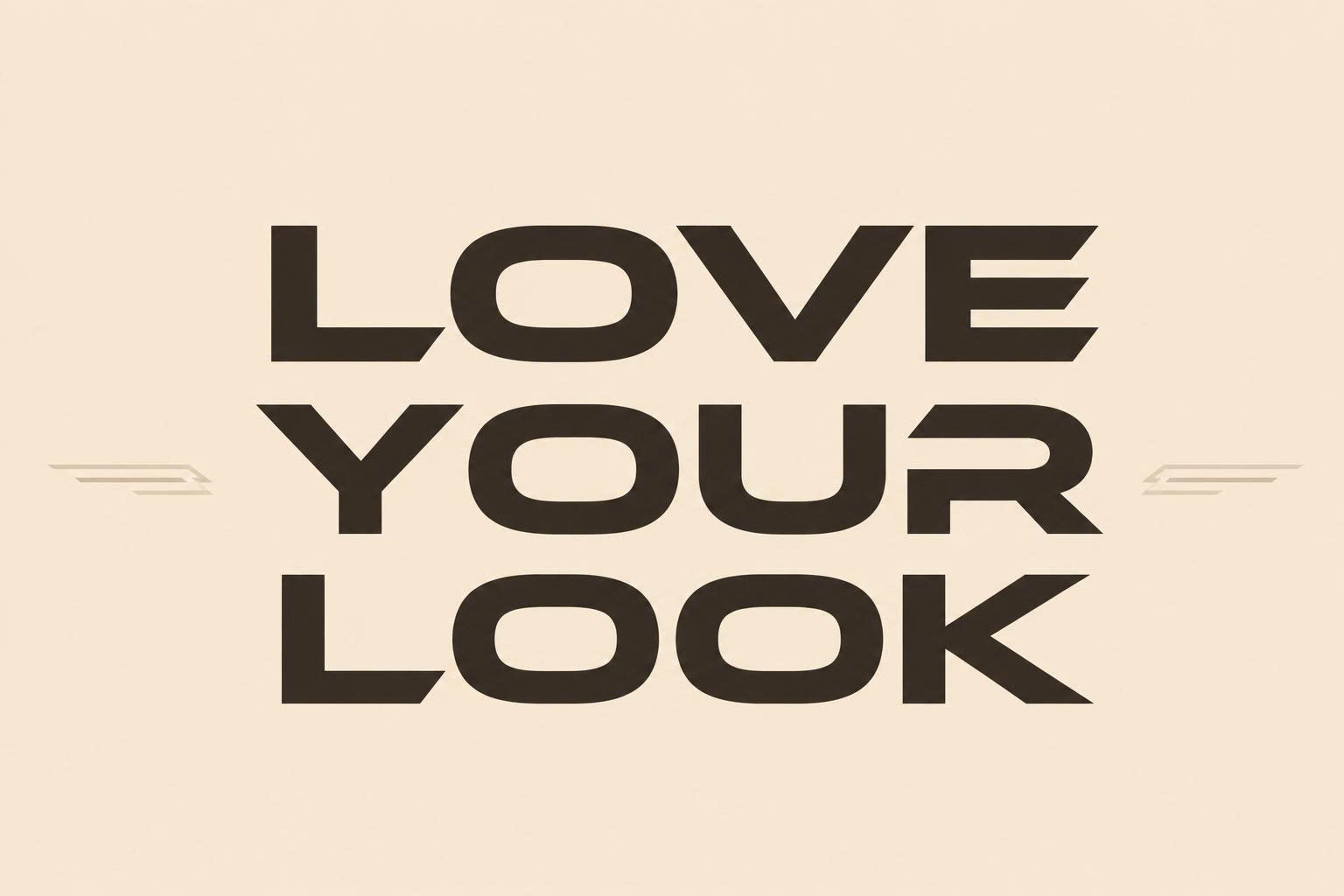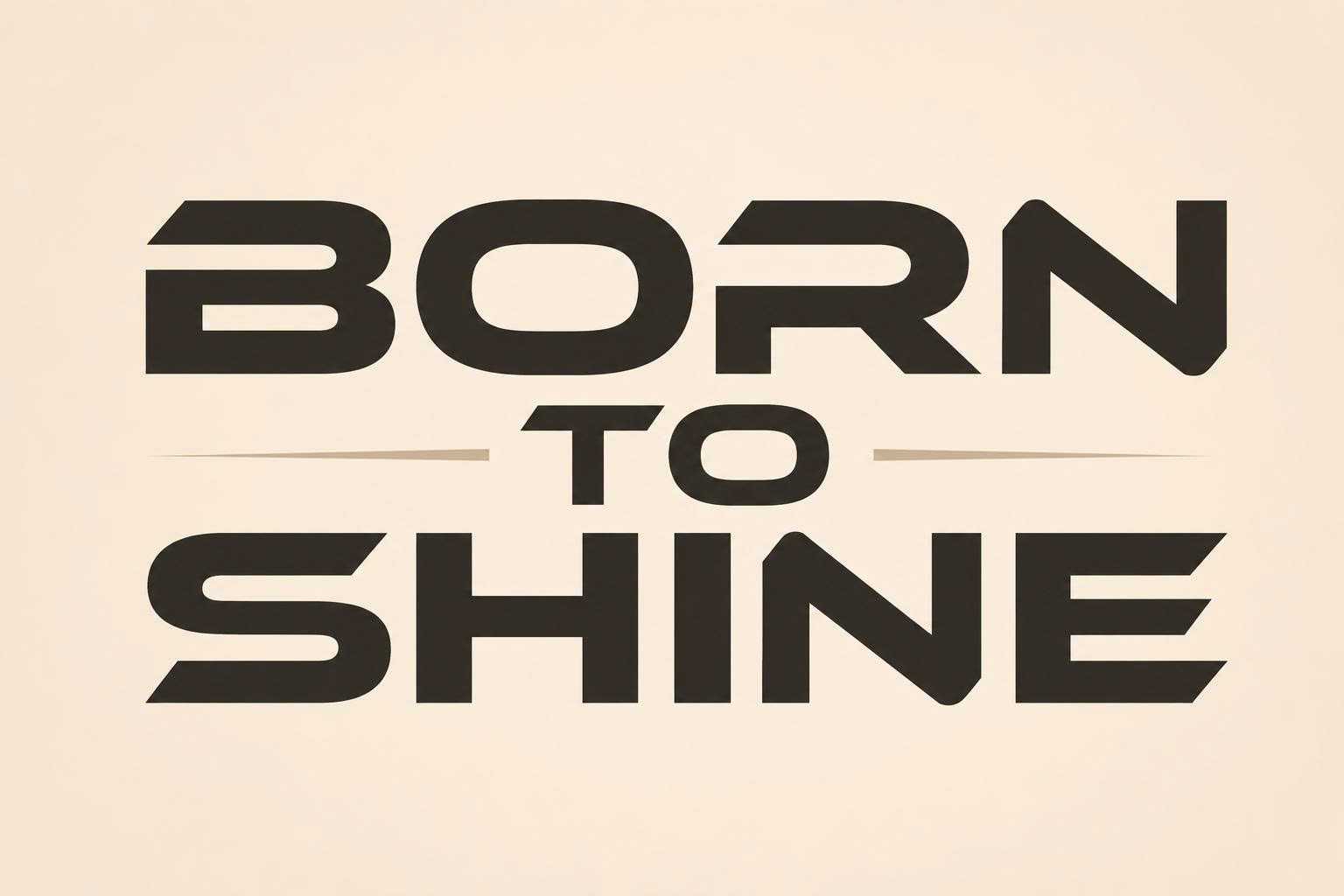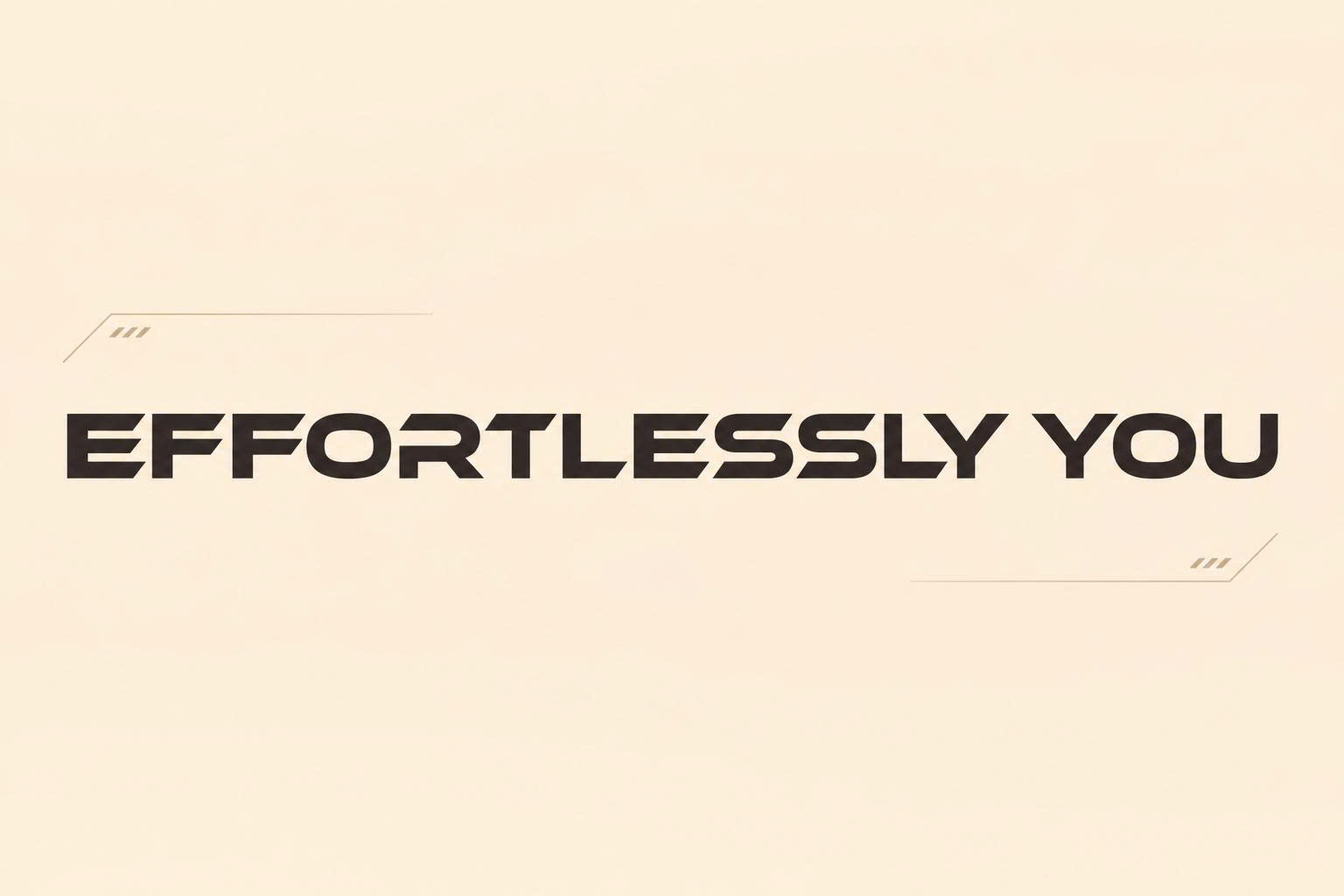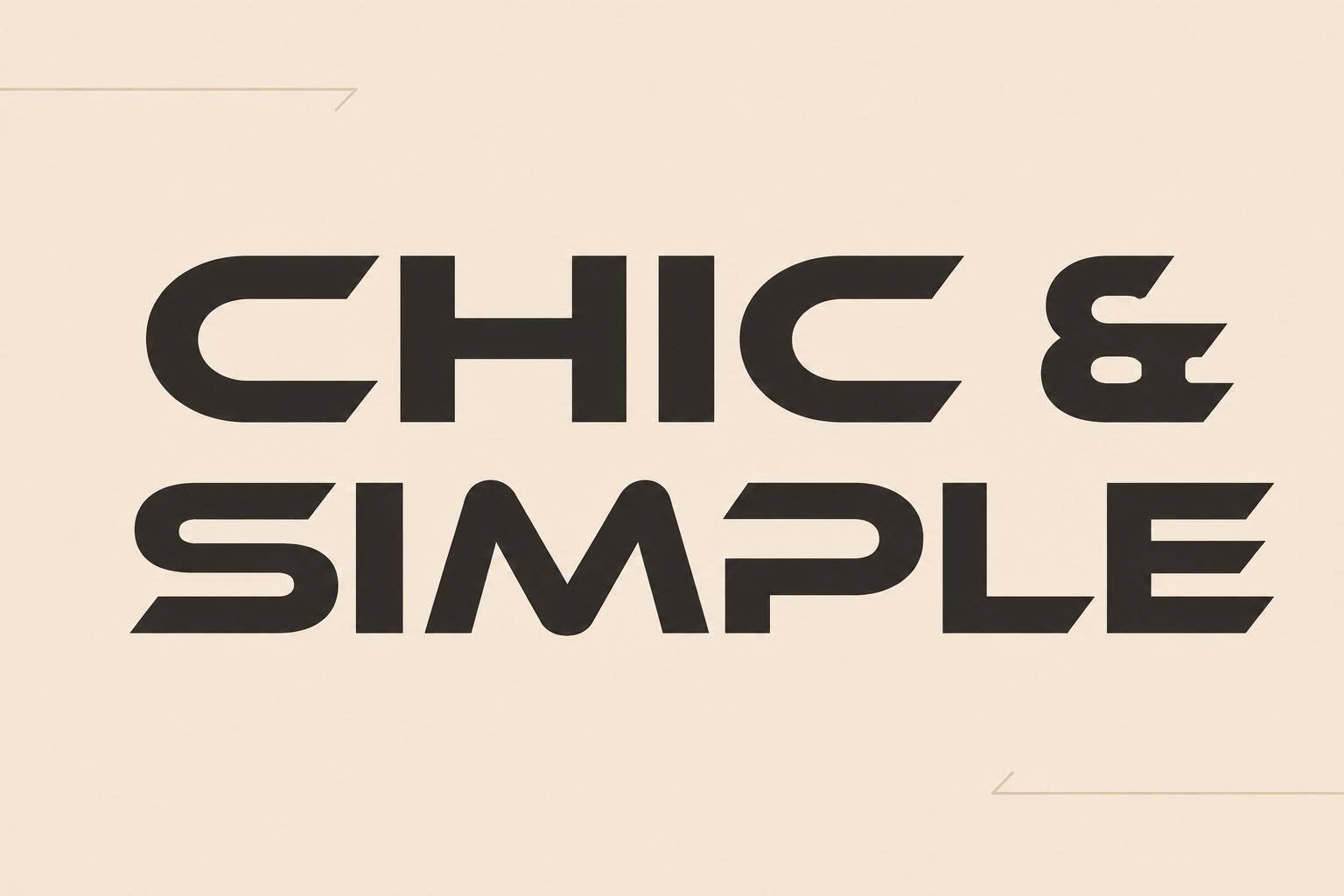
Ethnocentric Font Việt hóa là bộ phông chữ không chân (Sans-serif) mang phong cách viễn tưởng (Sci-fi) và hiện đại, nổi bật với cấu trúc hình học mở rộng và các đường nét cắt xẻ táo bạo. Với diện mạo đầy tính công nghệ và tương lai, Ethnocentric là lựa chọn hàng đầu cho các thiết kế logo công ty kỹ thuật số, poster phim hành động hoặc bao bì sản phẩm điện tử cao cấp. Doozypack.vn cung cấp link tải font Ethnocentric Việt hóa chuẩn, giúp bạn sở hữu bộ font Ethnocentric tiếng Việt không lỗi dấu để hiện thực hóa những ý tưởng thiết kế đột phá.
Đặc điểm thiết kế của font Ethnocentric Việt hóa
Ethnocentric không chỉ là một phông chữ hiện đại thông thường, nó mang trong mình hơi thở của kỷ nguyên số và sự đổi mới không ngừng.
Phong cách futuristic và hình học mạnh mẽ
Đặc trưng lớn nhất của font Ethnocentric Việt hóa là cấu trúc chữ cực rộng (Ultrawide) kết hợp với các góc bo tròn và những đường vát phẳng dứt khoát. Thiết kế này tạo nên sự vững chãi, uy lực và rất thu hút thị giác. Khoảng trắng bên trong các ký tự được tối ưu hóa để tạo cảm giác thông thoáng, giúp bản thiết kế trông cực kỳ “high-tech” và sang trọng.
Hệ thống dấu tiếng Việt được xử lý tinh tế
Các bộ font phong cách Sci-fi nước ngoài thường gặp lỗi nặng khi hiển thị tiếng Việt vì cấu trúc chữ rộng rất khó để đặt dấu thanh sao cho cân đối. Phiên bản font Ethnocentric tiếng Việt tại Doozypack.vn đã được điều chỉnh kỹ lưỡng, đảm bảo các dấu sắc, huyền, hỏi, ngã, nặng được tích hợp hài hòa vào khung hình học của chữ, giữ nguyên tinh thần mạnh mẽ của bộ font gốc.
Lời khuyên từ xưởng in: Vì Ethnocentric có cấu trúc chữ rất rộng (Wide), khi thiết kế tiêu đề trên hộp giấy, bạn nên lưu ý khoảng cách an toàn (Safe zone) ở hai bên mép hộp để tránh chữ bị che khuất khi gấp bao bì thực tế.
03 Lý do designer nên tải font Ethnocentric Việt hóa cho dự án?
Trong ngành thiết kế và sản xuất bao bì tại Doozypack.vn, Ethnocentric thường được các thương hiệu công nghệ ưu ái nhờ những ưu điểm sau:
- Tạo dấu ấn khác biệt: Ethnocentric giúp thương hiệu thoát khỏi sự an toàn của các font không chân truyền thống, khẳng định cá tính dẫn đầu và hiện đại.
- Khả năng nhận diện từ xa: Nhờ cấu trúc chữ rộng và nét đậm, font chữ này cực kỳ nổi bật trên các bảng hiệu hoặc mặt chính của hộp sản phẩm.
- Tối ưu cho sản phẩm kỹ thuật: Rất phù hợp cho các ngành hàng như linh kiện máy tính, phụ kiện ô tô, thiết bị thông minh hoặc bao bì game.
03 Ứng dụng của font Ethnocentric trong in ấn bao bì tại Doozypack.vn
Sự mạnh mẽ của Ethnocentric mang lại hiệu quả thị giác đặc biệt trên các ấn phẩm thực tế tại Doozypack.vn:
- Bao bì linh kiện điện tử: In tên sản phẩm trên vỏ hộp chuột gaming, bàn phím hoặc tai nghe tạo cảm giác hiện đại và đẳng cấp.
- Túi giấy công nghệ: Tên công ty sử dụng Ethnocentric in bằng kỹ thuật phủ UV định hình trên túi giấy Ivory mang lại vẻ ngoài vô cùng bắt mắt.
- Tem nhãn dán thiết bị: Phù hợp cho các tem thông số kỹ thuật hoặc nhãn hiệu dán trên các thiết bị gia dụng thông minh.
03 Lưu ý kỹ thuật khi in ấn với font chữ rộng như Ethnocentric
Sản xuất bao bì sử dụng font chữ hình học như Ethnocentric đòi hỏi designer cần lưu ý một số vấn đề tại xưởng in chuyên nghiệp:
- Kiểm soát Kerning (Khoảng cách chữ): Do các ký tự của Ethnocentric rất rộng, bạn nên điều chỉnh khoảng cách giữa các chữ cái thủ công để tránh việc văn bản trông quá rời rạc hoặc quá dính vào nhau.